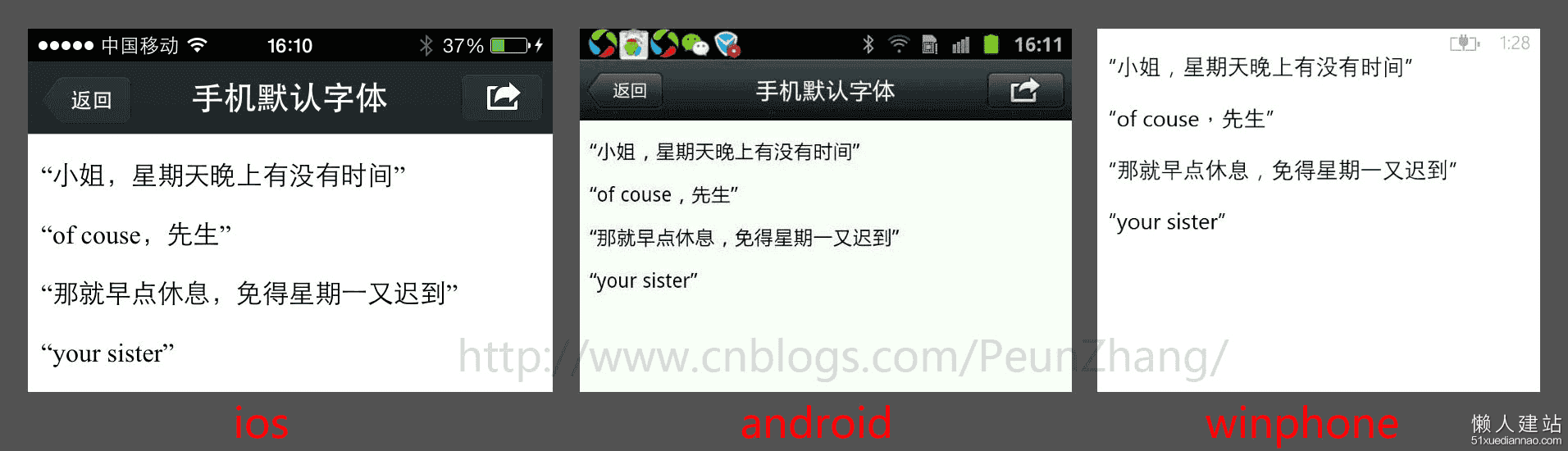
手机移动端web字体设置经验分享
pc端web设计通常使用微软雅黑字体,但是在手机移动端并没有微软雅黑字体,微软雅黑字体并不适合移动端web页面开发,下面列出手机端安卓/IOS系统的自带字体作为参考:
ios 系统自带字体
android 系统自带字体
Android默认中文字体是Droidsansfallback(华文中宋)
Android默认英文和数字字体是Droid Sans
无微软雅黑字体
winphone 系统
默认中文字体是Dengxian(方正等线体)
默认英文和数字字体是Segoe
无微软雅黑字体
在ios和android和winphone做个测试
下图为测试机 iphone 4s、三星 GT-N7000 android 2.3.6、HTC windows Phone 8.0 三种手机中的默认中文字体和英文字体展现:
我们可以看出三种不同的中文字体和微软雅黑一样是无衬线字体,有无衬线只是一个小原因,而无论页面中使用哪种字体,肉眼很难看出它们的差异,对产品的体验几乎没有影响。
使用系统默认的字体所达到的视觉效果跟使用微软雅黑字体没有明显的差别
结论
各个手机系统有自己的默认字体,且都不支持微软雅黑
如无特殊需求,手机端无需定义中文字体,使用系统默认
英文字体和数字字体可使用 Helvetica ,三种系统都支持
建议:英文和数字都设定为 Helvetica,因为在ios中默认的英文和数字是两种不同的字体,如果不设置成一种字体,显示效果不一样。